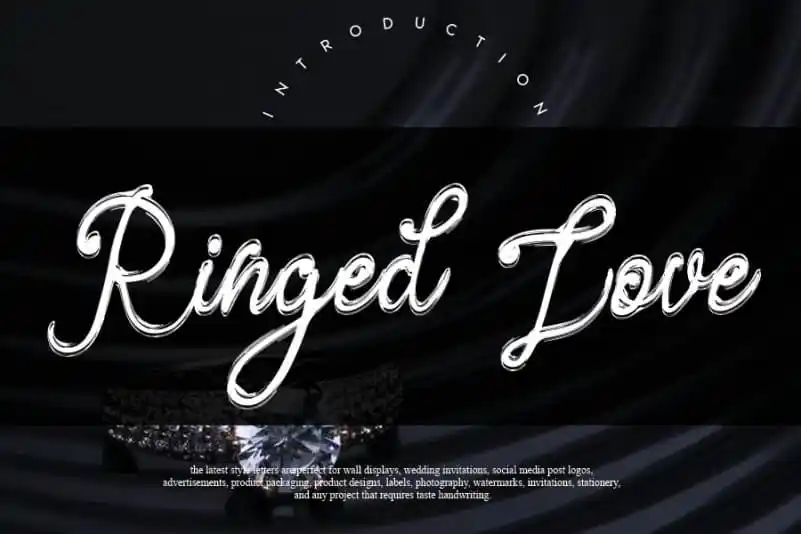
Ringed Love Handwritten Font
A ‘Ringed Love Handwritten Font’ é uma fonte de letra escrita a mão que transmite amor e elegância ao mesmo tempo. Criada pela equipe talentosa do andikastudio, esta fonte mantém os influentes traços do calligráfico, mas também se atualiza para um estilo contemporâneo e moderno. Ela é perfeita para aqueles que procuram uma fonte única capaz de dar ao seu design um toque de originalidade e sofisticação. Seja você um designer gráfico ou artista freelance, essa fonte será definitivamente um favoritismo para os projetos mais ambiciosos. Adquira-a agora e traga seus trabalhos à sua máxima excelência.